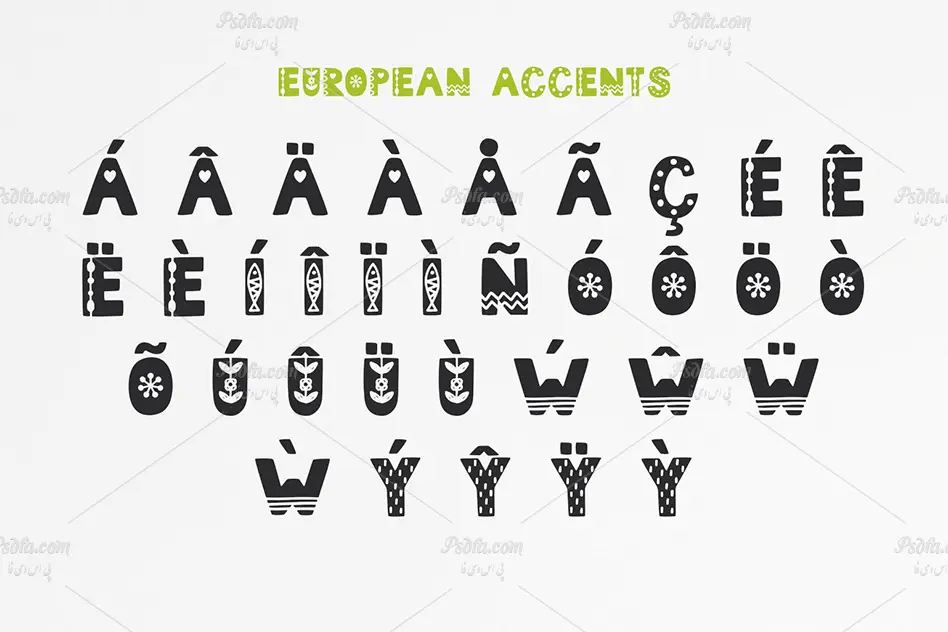
فونت انگلیسی کارتونی و فانتزی Roligt Scandinavian Kids مناسب برای طرح های کودکانه
فونت انگلیسی کارتونی و فانتزی
در این پست شاهد فونت انگلیسی کارتونی و فانتزی Roligt Scandinavian Kids مناسب جهت استفاده در طرح های کودکانه می باشید. این فونت زیبا در قالب یک فایل otf در سایت بارگذاری شده است که پس از نصب این فایل در پوشه فونت های سیستم قادر به استفاده از آن در تمام نرم افزارهای گرافیکی و ویرایشگر متن از جمله نرم افزار فتوشاپ ، ایلاستریتور ، مجموعه نرم افزار آفیس و … خواهید بود. از این فونت که به صورت فانتزی طراحی شده است می توان در طراحی بر روی انواع پارچه و لباس ویژه کودکان ، طراحی انواع قاب عکس ، طراحی ظروف سلولزی ، طراحی بسته بندی محصولات ، طراحی انواع پوستر ، تراکت و … استفاده نمود.